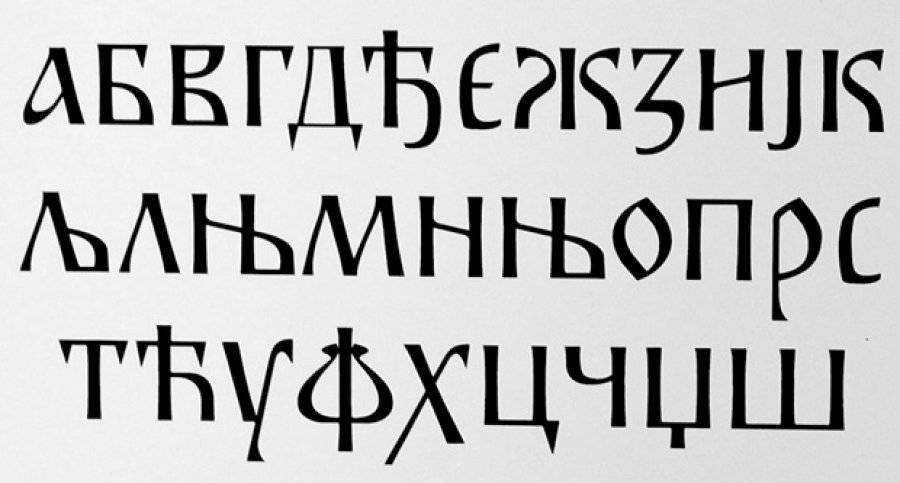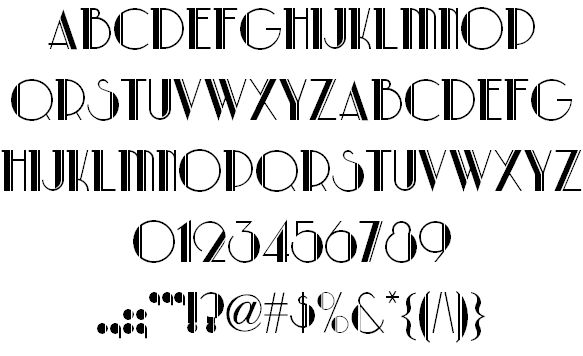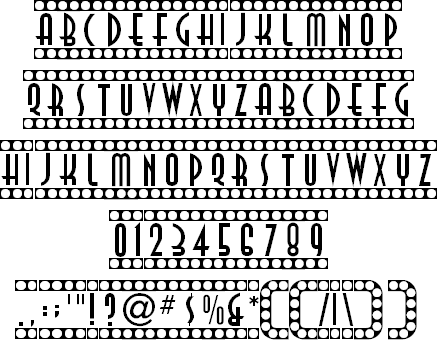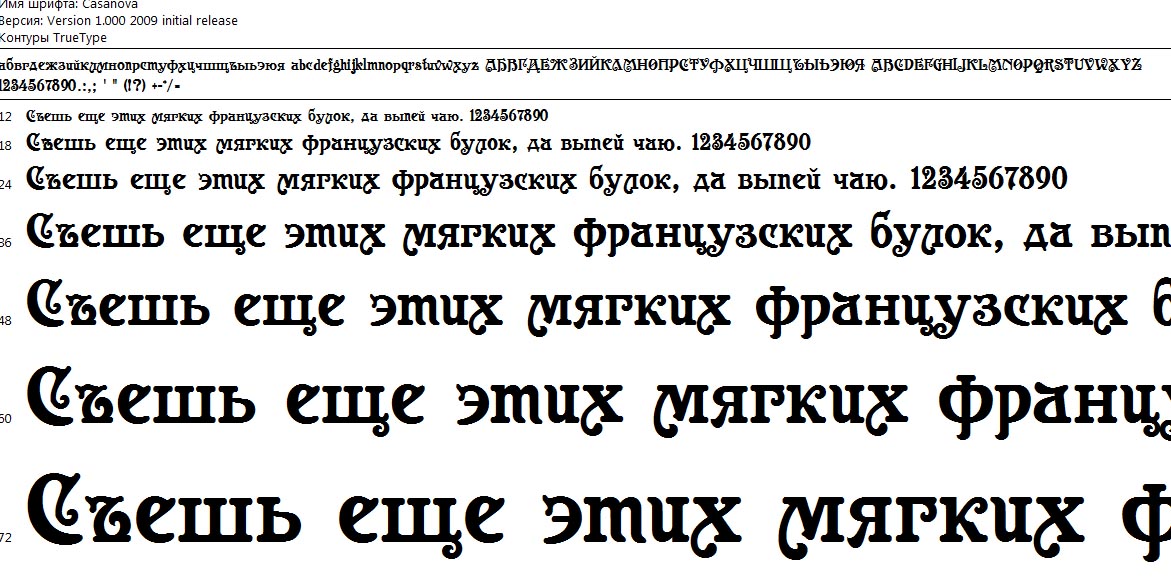
Руководство по 10 качествам шрифтов и их применению в дизайне
Шрифты играют важнейшую роль в дизайне: создают настроение, внушают эмоции, помогают восприятию образа еще до прочтения текста. Это тайные агенты визуальной коммуникации, работающие с подсознанием зрителя.
В этом руководстве описано какие шрифты стоит использовать для разных индустрий, и как даже самые небольшие шрифтовые детали меняют отношение к написанному.
1. Насыщенность
Жирность (Weight) шрифта мы замечаем в первую очередь и в любых условиях. Основные типы насыщенности: светлый, нормальный и жирный. Нормальные начертания (Regular) эмоционально нейтральны, на них меньше всего влияют оптические искажения или плохая резкость.
Лучше всего распознается графема, поэтому нормальная насыщенность идеальна для чтения. Более эмоционально значимыми являются светлые и жирные начертания, передающие гамму ощущений от робкой деликатности до настойчивой грубости.
Начертания Thin, Regular, Black гарнитуры Kazimir Text.
Тонкие начертания (Thin, Light) приятно рассматривать как линейный рисунок. Такая надпись не привлечет внимания, если вы сами этого не захотите, ее можно «выключить» просто отведя взгляд. Отсюда ощущение деликатности и бережности. Не удивительно, что такие начертания распространены в косметической отрасли и во всем, что близко к телу, от белья до носимых гаджетов.
Полужирные начертания (Semibold) содержат максимум уникальности формы, сохраняют читабельность и добавляют значимости тексту. Поэтому их используют для выделений в тексте, а также в логотипах.
Жирные начертания (Bold) созданы для привлечения внимания к коротким надписям. Читать их не очень удобно, но у вас нет выбора. Ведь уделив много внимания предмету, ваш мозг узнает о нем как можно больше.
Сверхжирные шрифты (Black) создают ощущение тяжести, мощи и усиливают собственные качества шрифта, для передачи которых более нейтральным начертаниям не хватало веса. Такие начертания провоцируют быстрый эмоциональный отклик, поэтому их часто применяют: в играх, рекламе, шоу-бизнесе.
2. Ширина
Ширина (Width) знаков шрифта, как и насыщенность, различается быстро и сильно влияет на читабельность и заметность надписи. Начертания нормальной ширины оптимальны для чтения, а другие варианты: узкие и широкие очень специфичны и несут отчетливую эмоциональную окраску.
Сверхузкий шрифт – Reforma Grotesk Medium, шрифт нормальной ширины – Pragmatica Book, сверхширокий шрифт – Europe Extended.
Слегка зауженные начертания тоже могут быть читабельными. Компактные версии текстовых шрифтов используются там, где нужно вместить много текста в небольшую строку. Но этот прием создает легкое ощущение тесноты и экономности.
У сверхузких начертаний более интересные особенности.
На них очень легко обратить внимание, из-за вертикальных линий, которые начинают преобладать в надписи. Кажется, что кто-то высокий забрался на трибуну и заводит толпу. Из-за низкой читабельности узких букв такой шрифт может передавать лишь краткие слова исключительной важности. Поэтому сверхузкие шрифты органично смотрятся там, где нужен стоп-эффект: в объявлениях, газетных заголовках, агитации.
Широкие и сверхширокие начертания сильно меняют восприятие текста. В широких шрифтах форма букв изменяется, появляется больше горизонталей. Даже короткое слово начинает читаться медленно, становится важным и запоминающимся. Все вокруг надписи кажется изобильным и внушительным. Широкие начертания прекрасно читаются под углом или при скоростном движении – перспектива нормализует пропорции. Поэтому, такие шрифты часто используют производители машин, самолетов и спортивных товаров.
3. Контраст
Разница толщины основных и дополнительных штрихов называется контрастностью шрифта. Контраст определяет положение шрифта на шкале читабельность / эстетичность.
Слабый и средний контраст помогает при длительном чтении и не всегда создает особое настроение, зато крайние значения: нулевой и сильный контраст, формируют отчетливые художественные образы.
Неконтрастный шрифт – Stem, шрифт со средним контрастом – PT Serif, максимальный контраст – DietDidot.
При полном отсутствии контраста надпись выглядит просто и лаконично, иногда даже примитивно. Неконтрастные шрифты разрывают связь набора с ручным письмом, опираясь на индустриальную и постиндустриальную городскую эстетику в любых ее проявлениях, от палочных шрифтов до неоновых вывесок. Эти особенности делают неконтрастные шрифты отличным решением для всех, кто хочет выглядеть современно и прогрессивно.
Очень сильный контраст – художественный прием, характерный для шрифтов романтизма и классицизма. Контрастные шрифты жертвуют читабельностью ради красоты титульного листа, обложки или плаката. Чередование толстых и тонких линий напоминает драматическое противостояние силы и слабости, льда и пламени, а соединение контрастных штрихов создает изящный силуэт и ритм, напоминающий музыку или танец.
Я шел по улице, рассматривая архитектуру зданий в районе Марины, когда увидел сетку на крыше. Один из рабочих положил на них доску, и произошло волшебство. Голливуд 69 теперь свободен с 99!
Стиль письма показывает влияние раннего ар-деко, но ручная надпись была сделана в конце 1920-х годов, ближе к концу периода ар-нуво.